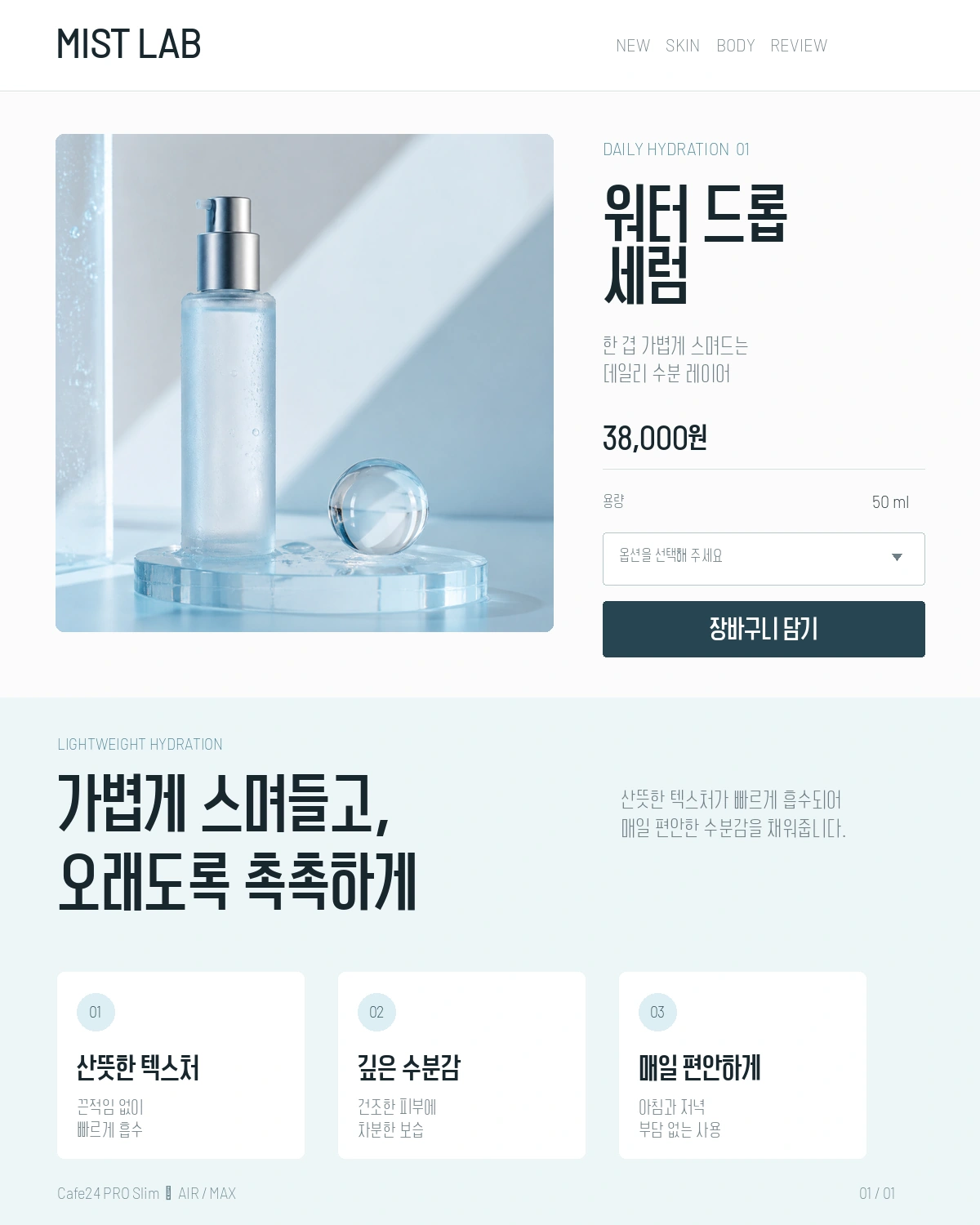
카페24 PRO Slim — 카페24에서 배포하는 무료 폰트입니다. 폭을 좁고 길게 뽑아 세련된 인상을 내는, 대행 서비스와 짝을 이루는 디스플레이 고딕체
카페24가 2025년 11월에 내놓은 서체로, 자사 대행 서비스 카페24 PRO와 짝을 이루는 전용 글꼴입니다. 카페24는 이 서체에도 별도 설명문을 붙이지 않아 제작사가 밝힌 것은 프로·슬림·세련된이라는 태그와 스타일별 견본 문장뿐인데, 그 문장들이 사실상 각 스타일의 성격을 말해 줍니다. Max는 한 글자에도 임팩트를 담는 쪽, Fit은 균형을 잡아 정돈하는 쪽, Air는 가볍게 시작하는 쪽입니다.
이름의 슬림이 형태에 그대로 드러납니다. 파일에서 재어 보면 낱자가 폭보다 높이가 커서 세로로 선 인상이고, 받침 유무에 따른 높이 차는 거의 없는 네모틀입니다. 가로세로 획 굵기 차이가 20% 안쪽인 고른 민부리라 인상이 깔끔합니다.
Max와 Fit, Air 세 가지로 나오는데 카페24는 이 셋을 굵기 단계가 아니라 각각 별개 패밀리처럼 배포합니다. 파일도 따로 내려받아야 합니다. 수록 글자는 2,780자로 흔히 쓰는 낱말은 다 나오지만 드문 음절에서는 네모가 뜰 수 있습니다.